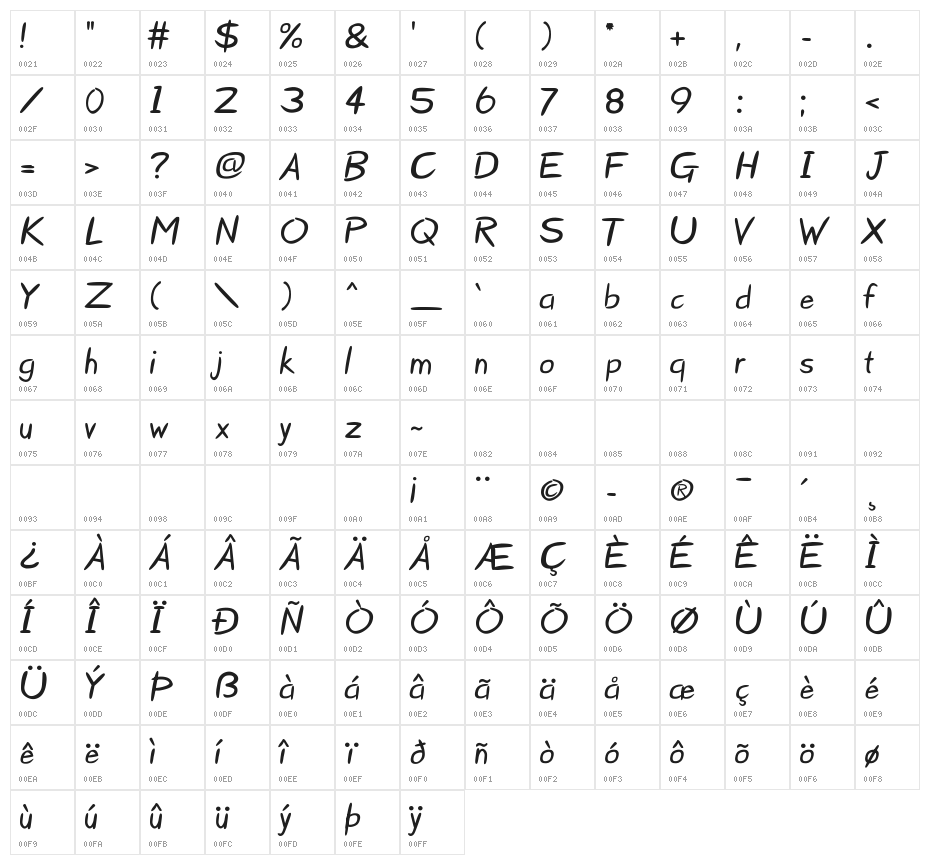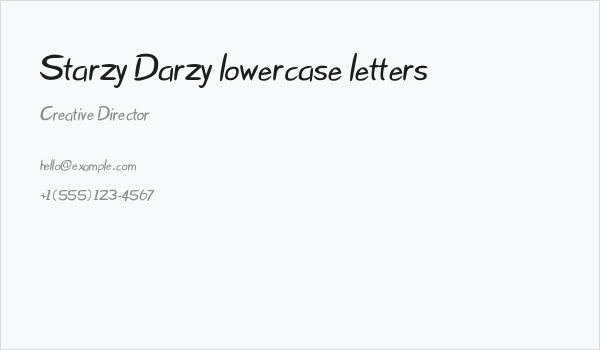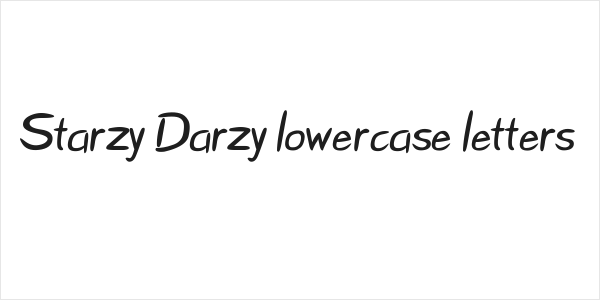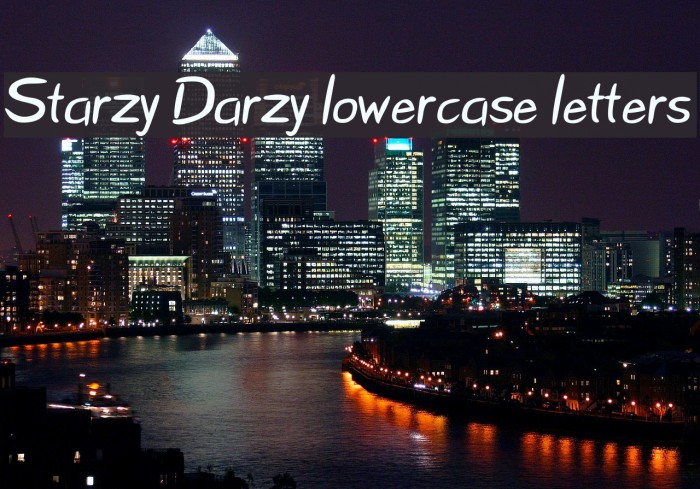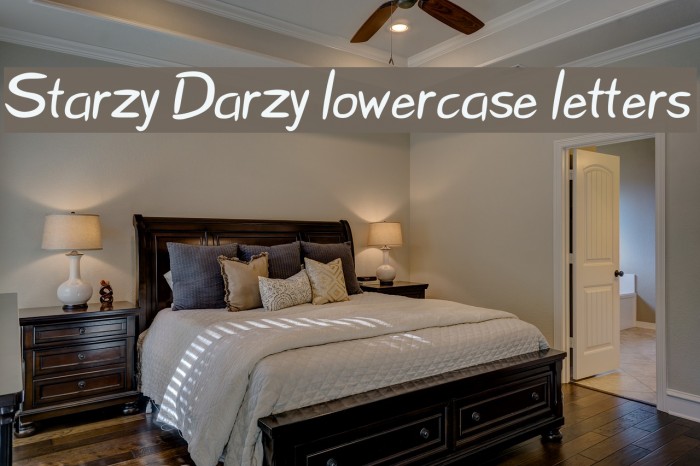
Starzy Darzy lowercase letters Font
| Style général | Playful |
| Cas d'utilisation | Headlines, Logos, Invitations |
| Projets proposés | Ideal for children's books, greeting cards, playful branding, and casual invitations. |